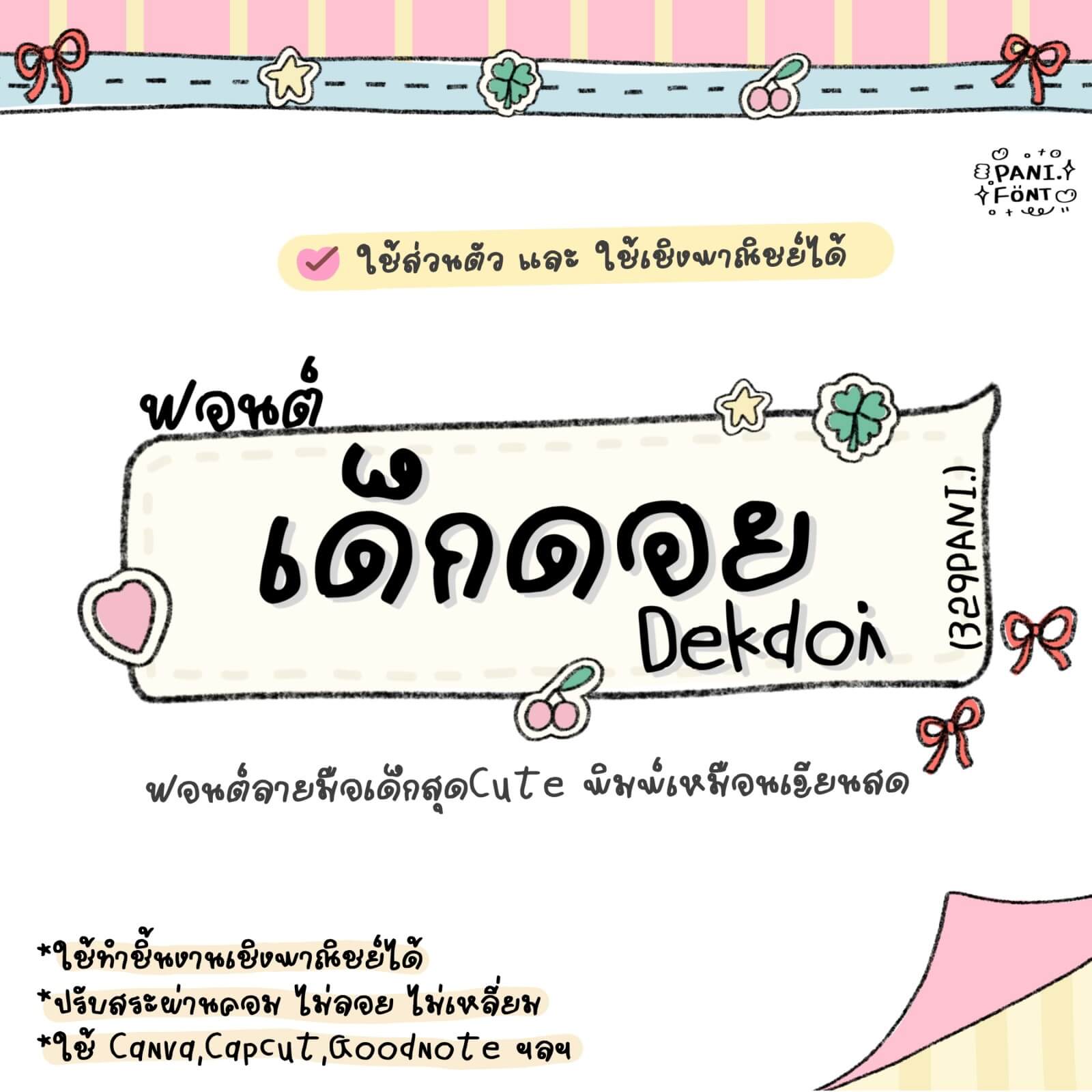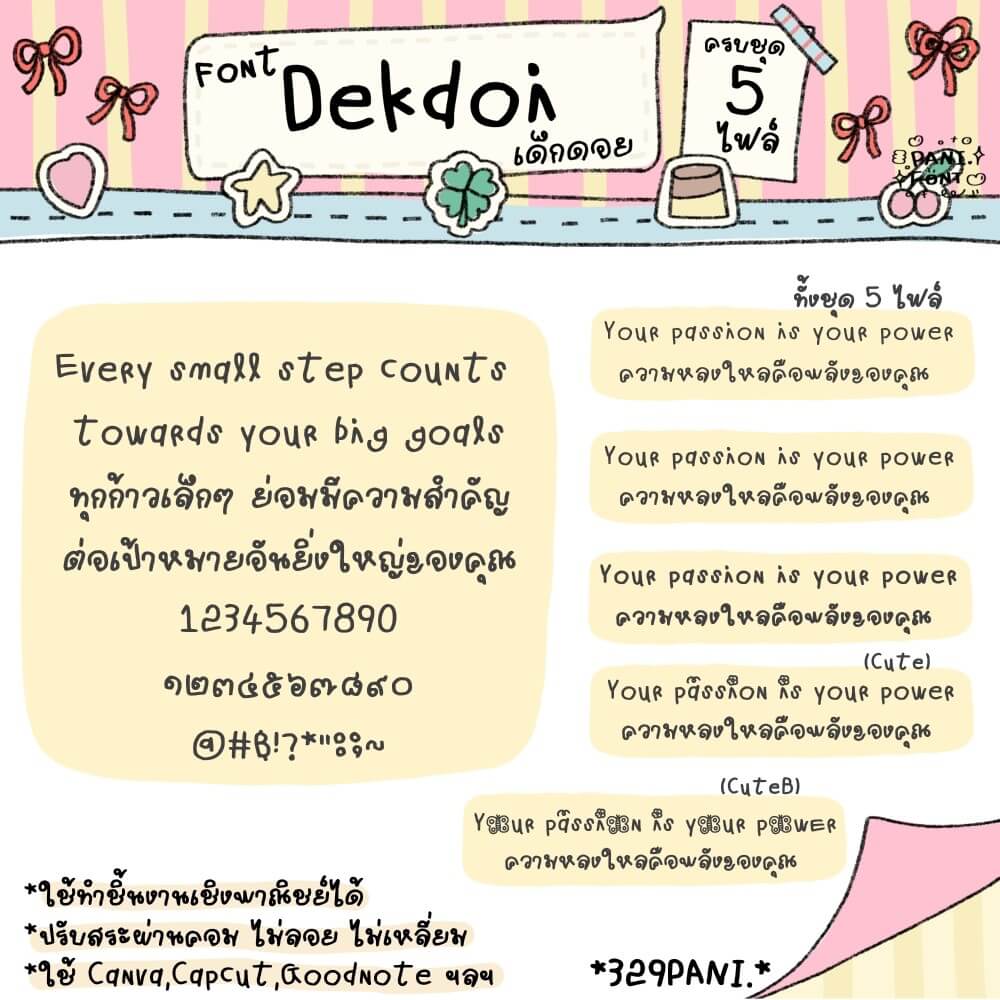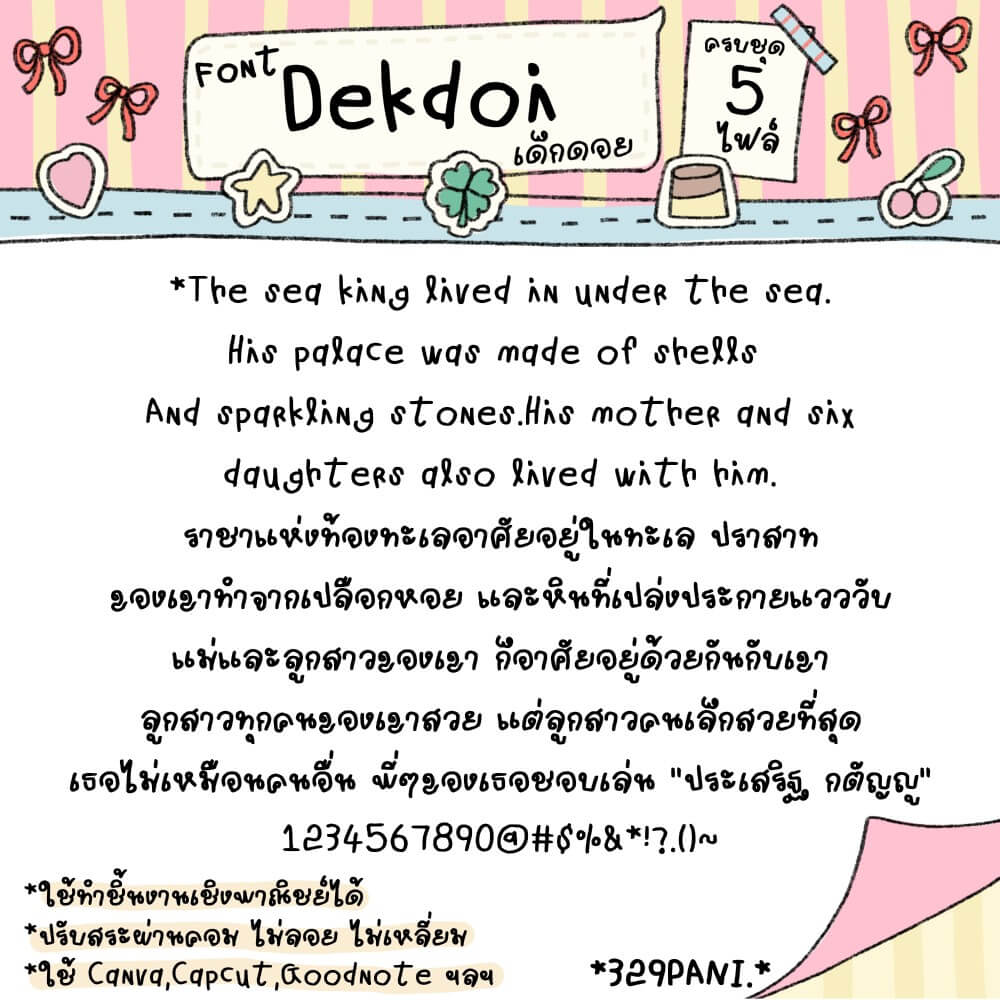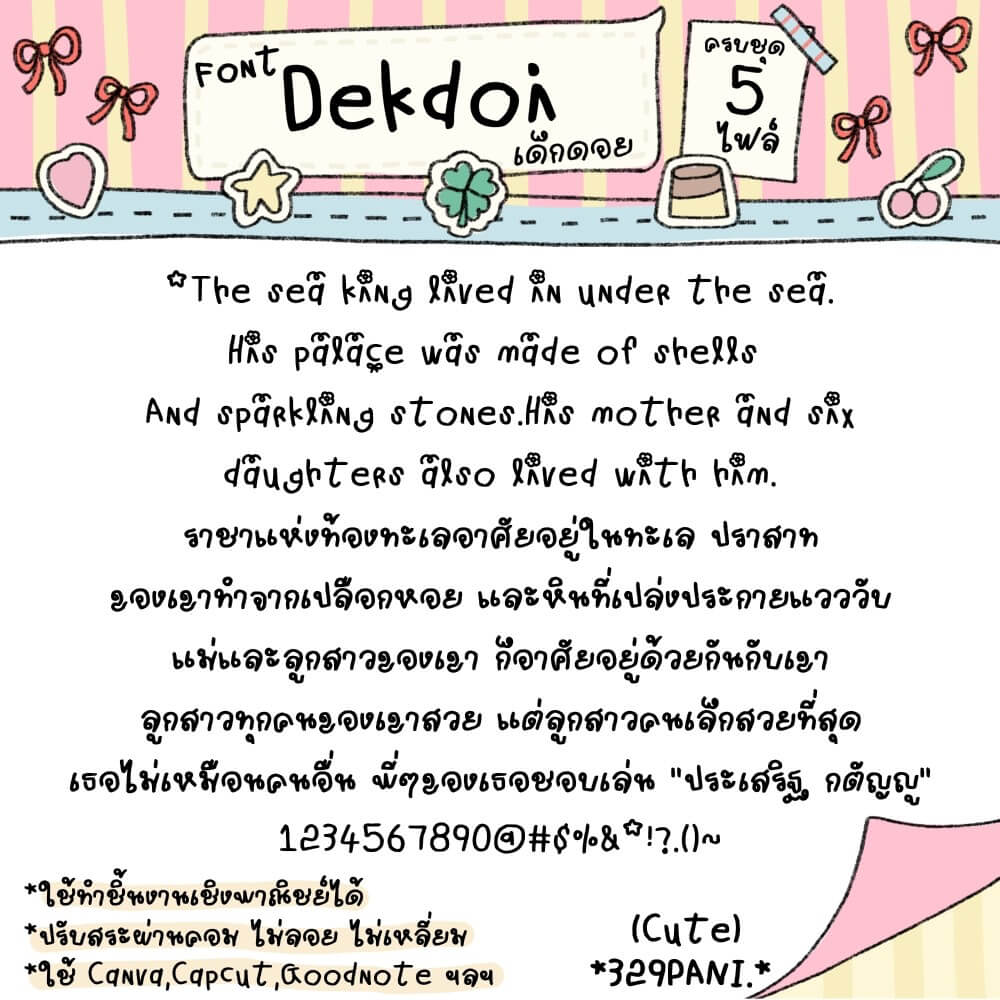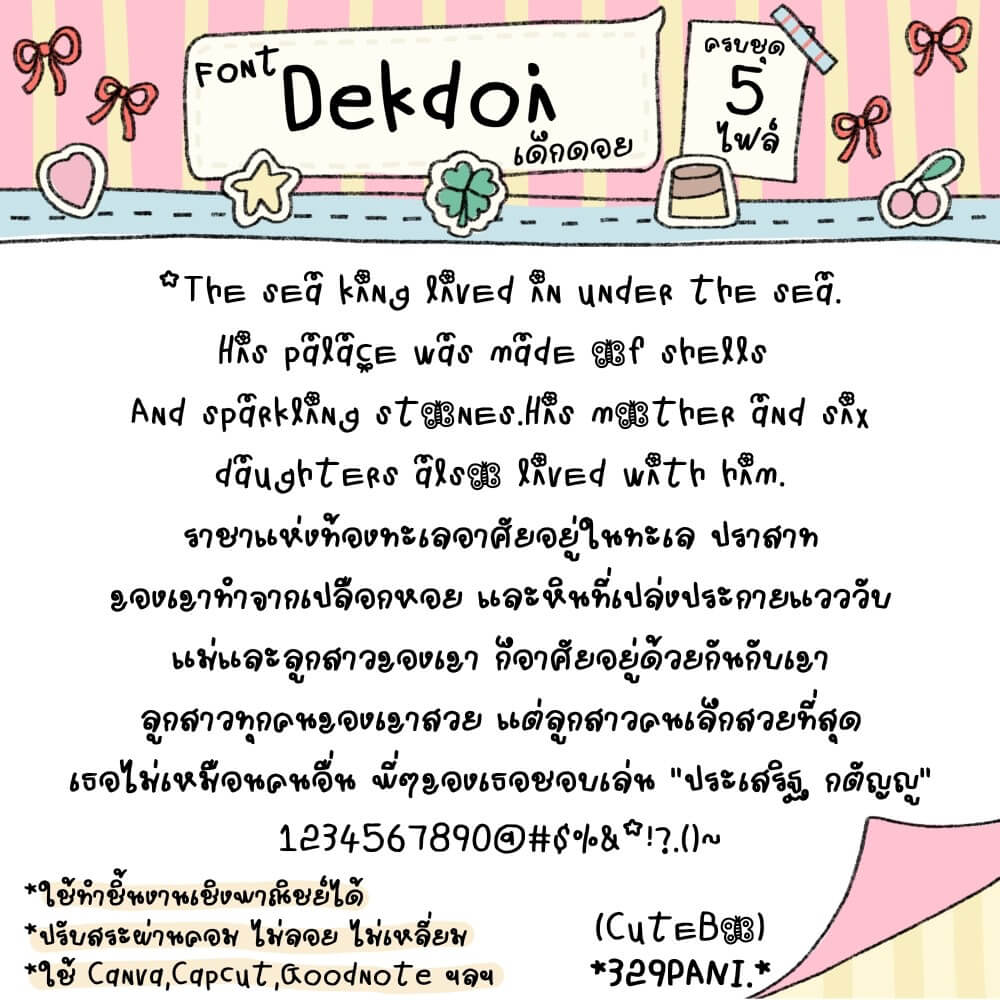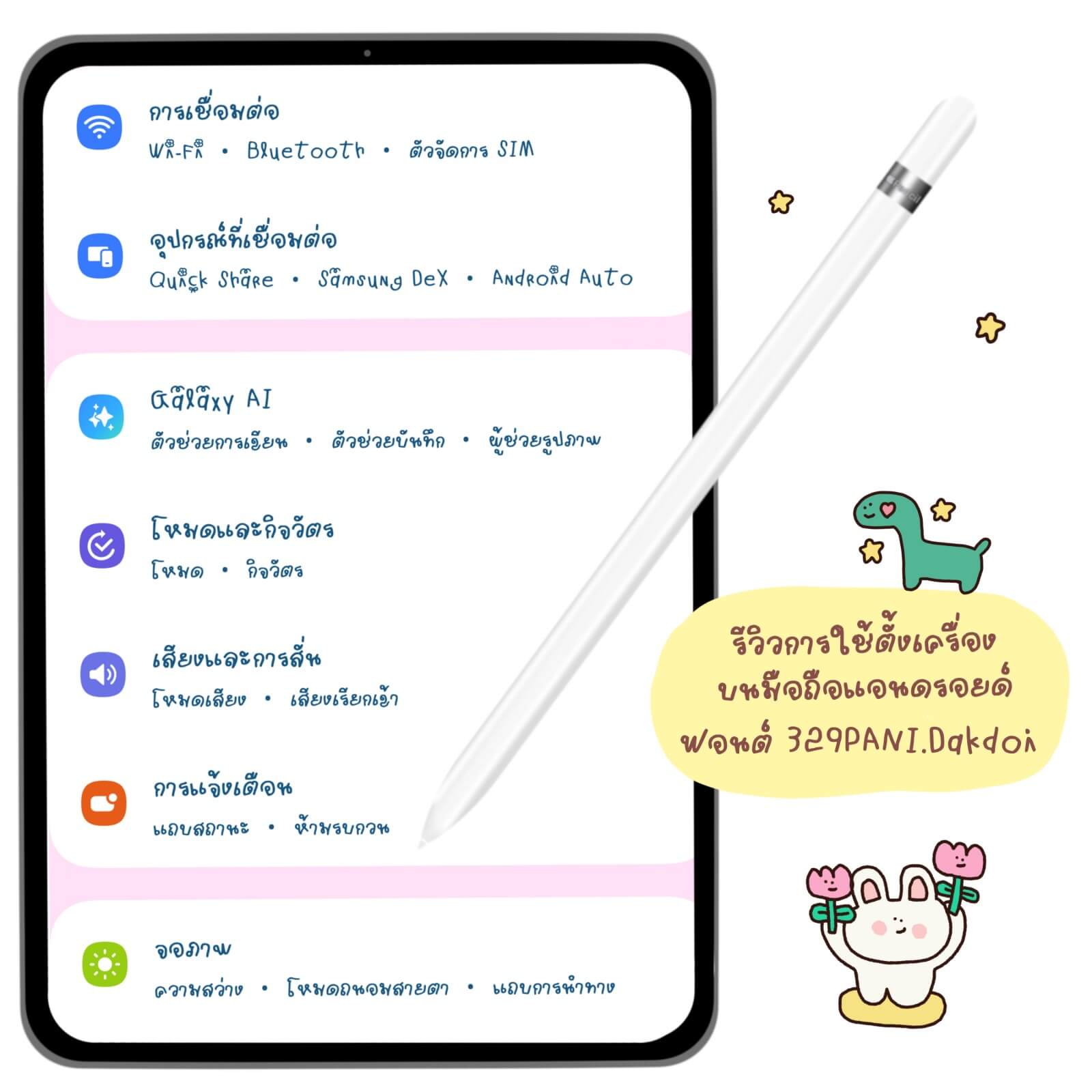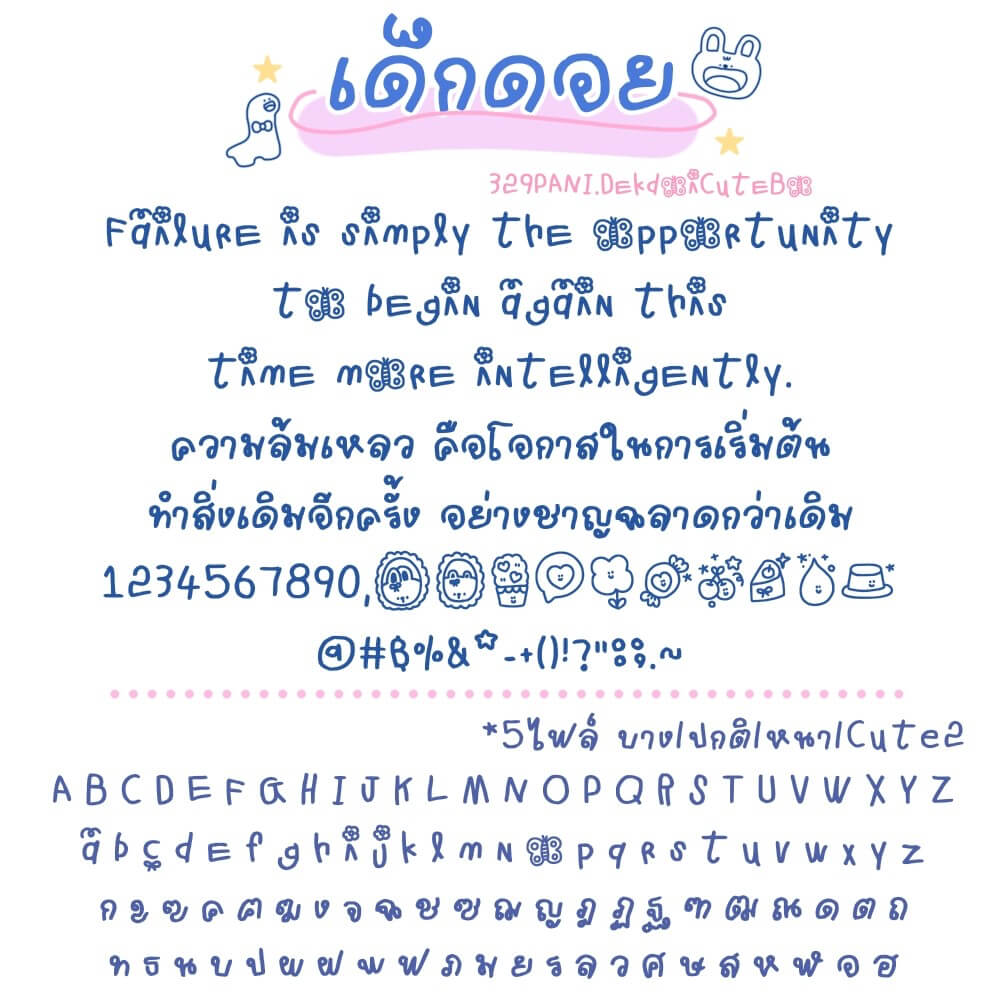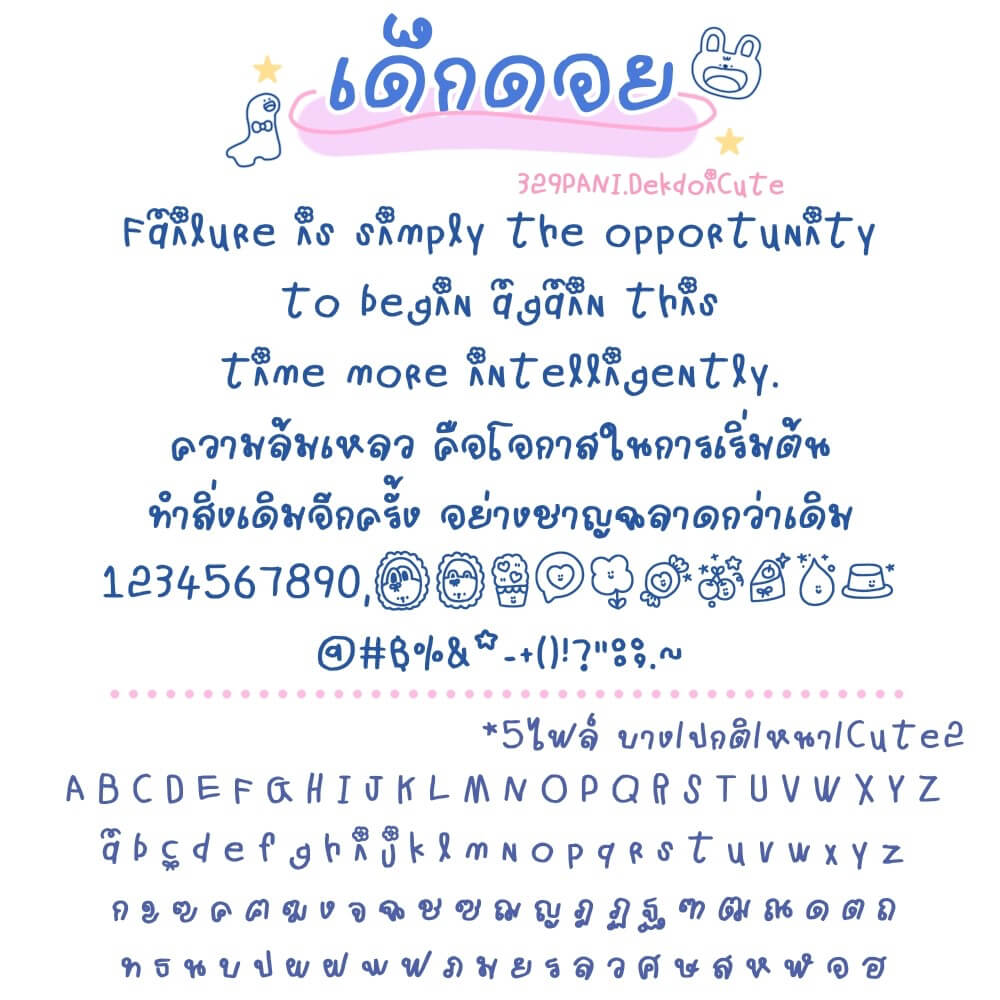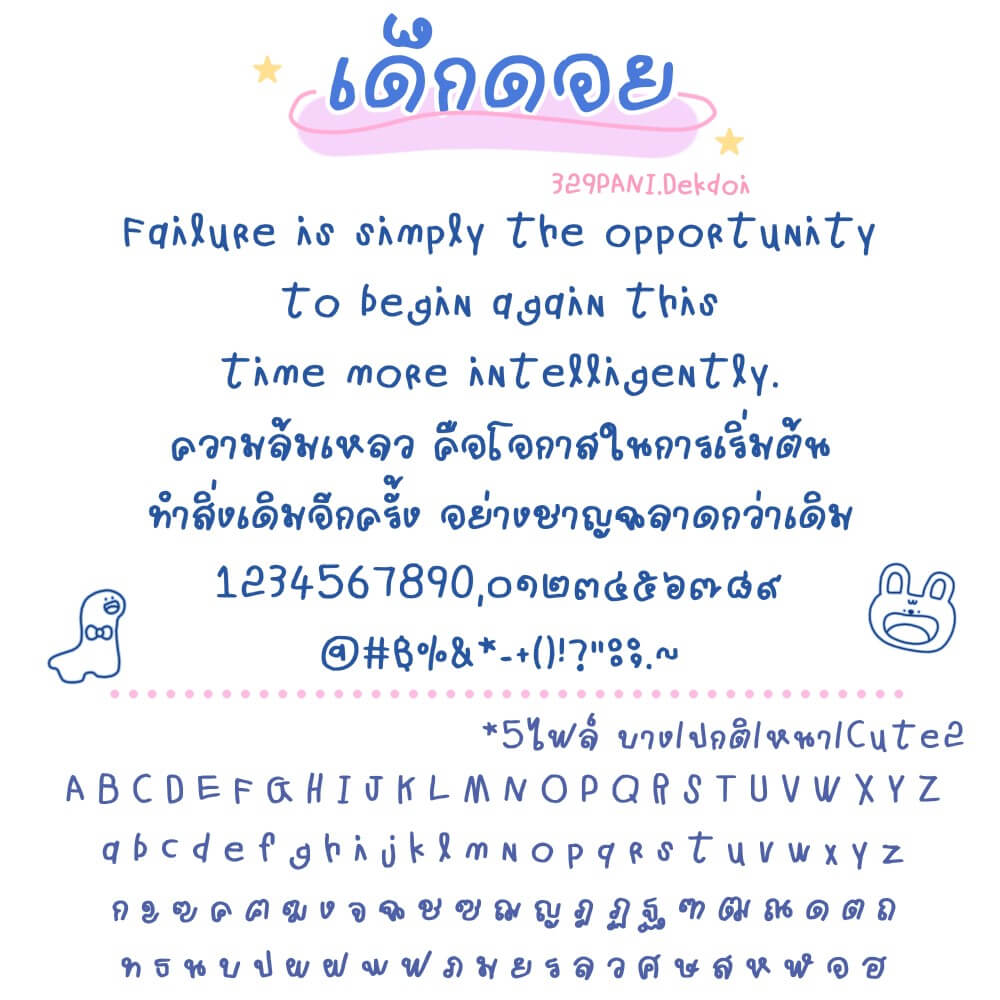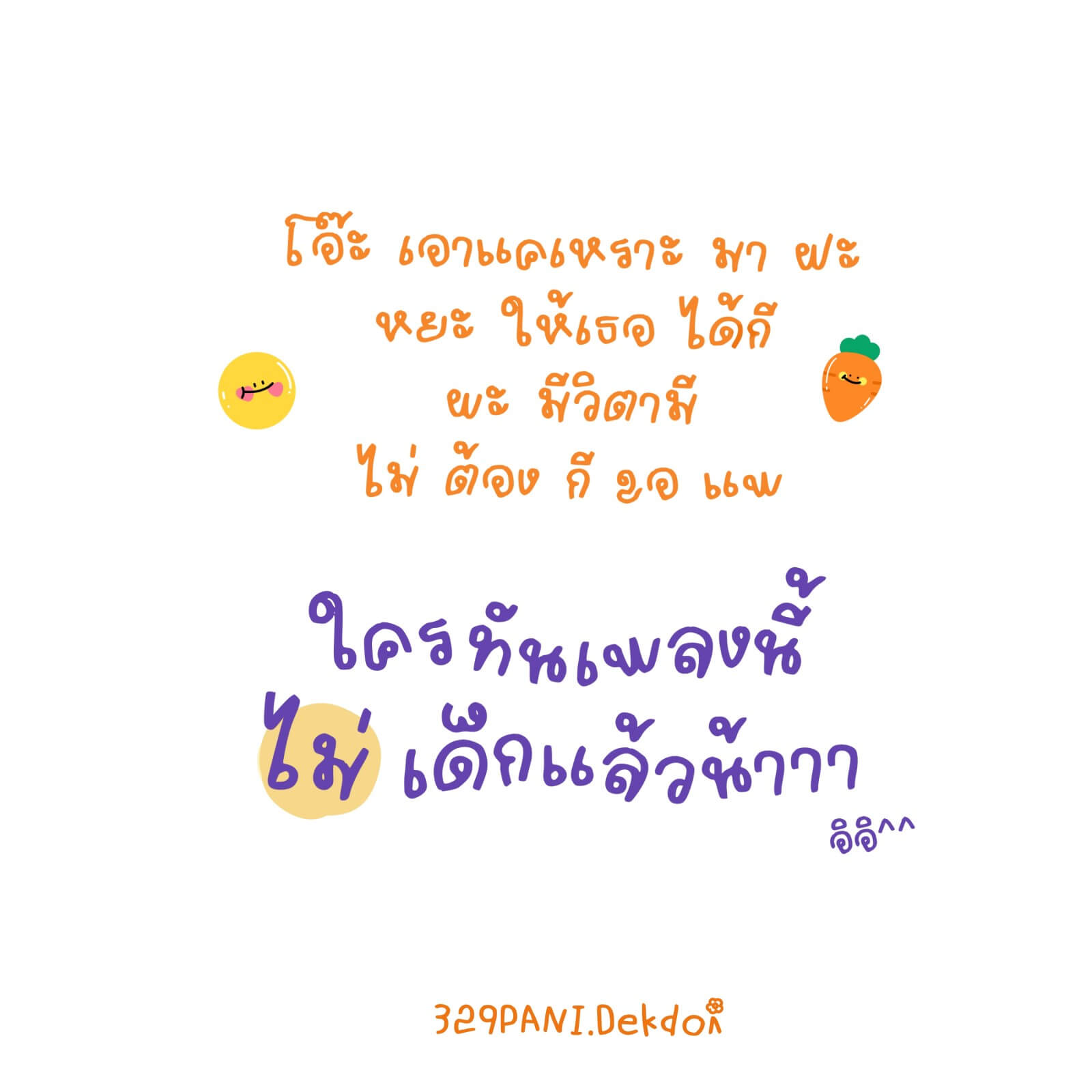
ฟอนต์ 329PANI.Dekdoi – โหลดทดลองใช้ฟรีตัว Demo ใครชอบแนว ลายมือเด็ก หรือแต่งรูป แต่งคลิป ทำคอนเทนต์ คือน่ารัก หรือจะเอาไว้จดใน Goodnote ก็เหมือนเขียนสด เหมือนเขียนเอง รับรอง ชุดนี้ไม่ผิดหวัง
*เลขไทยมีอีโมจิ ไว้แต่งรูปด้วยค่ะ
ฟอนต์มี 5 ไฟล์ – น้ำหนัก บาง ปกติ หนา Cute CuteB
*ตัวCute เลขไทยเป็นอีโมจิ
เด็กดอย (329PANI.Dekdoi)